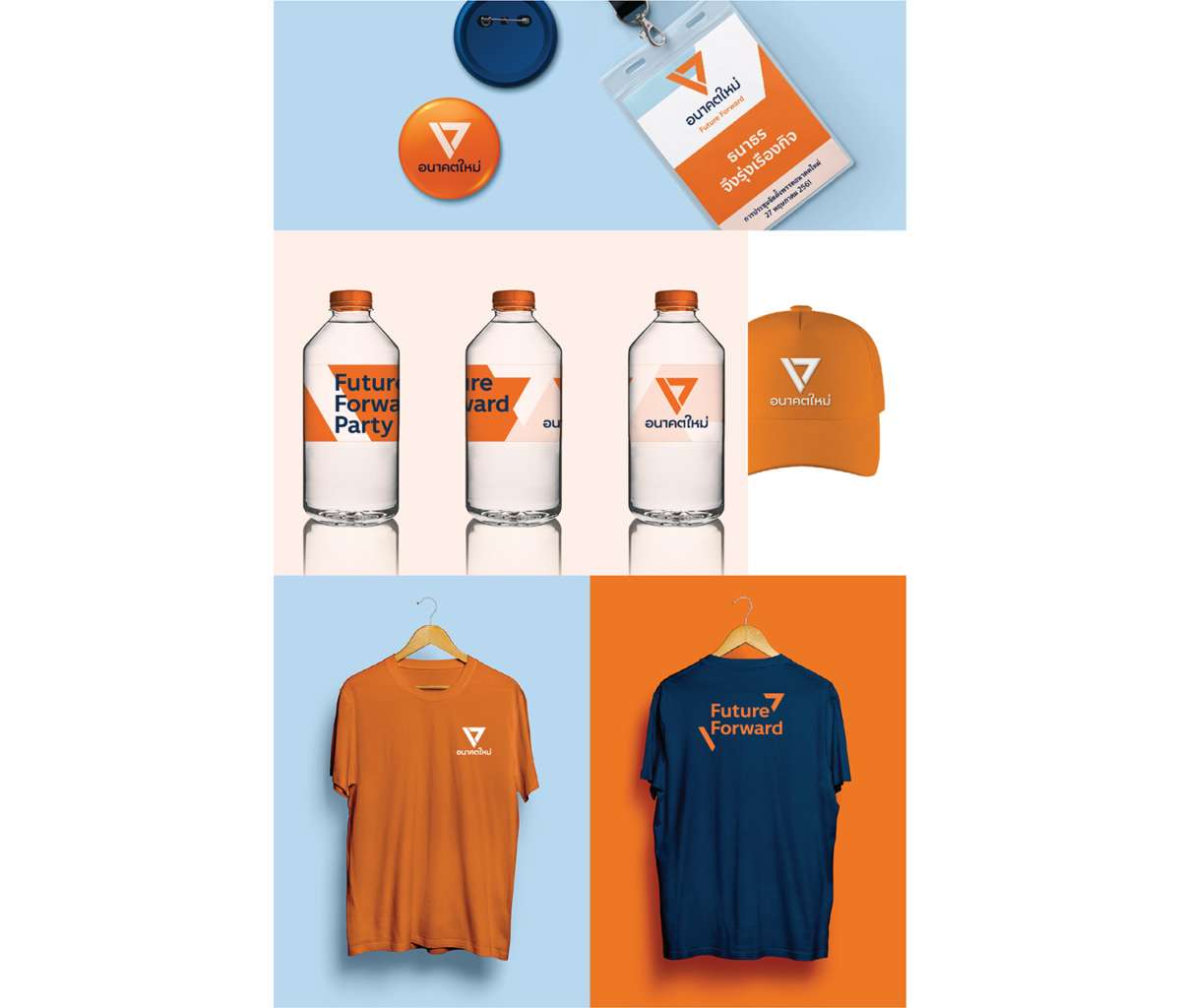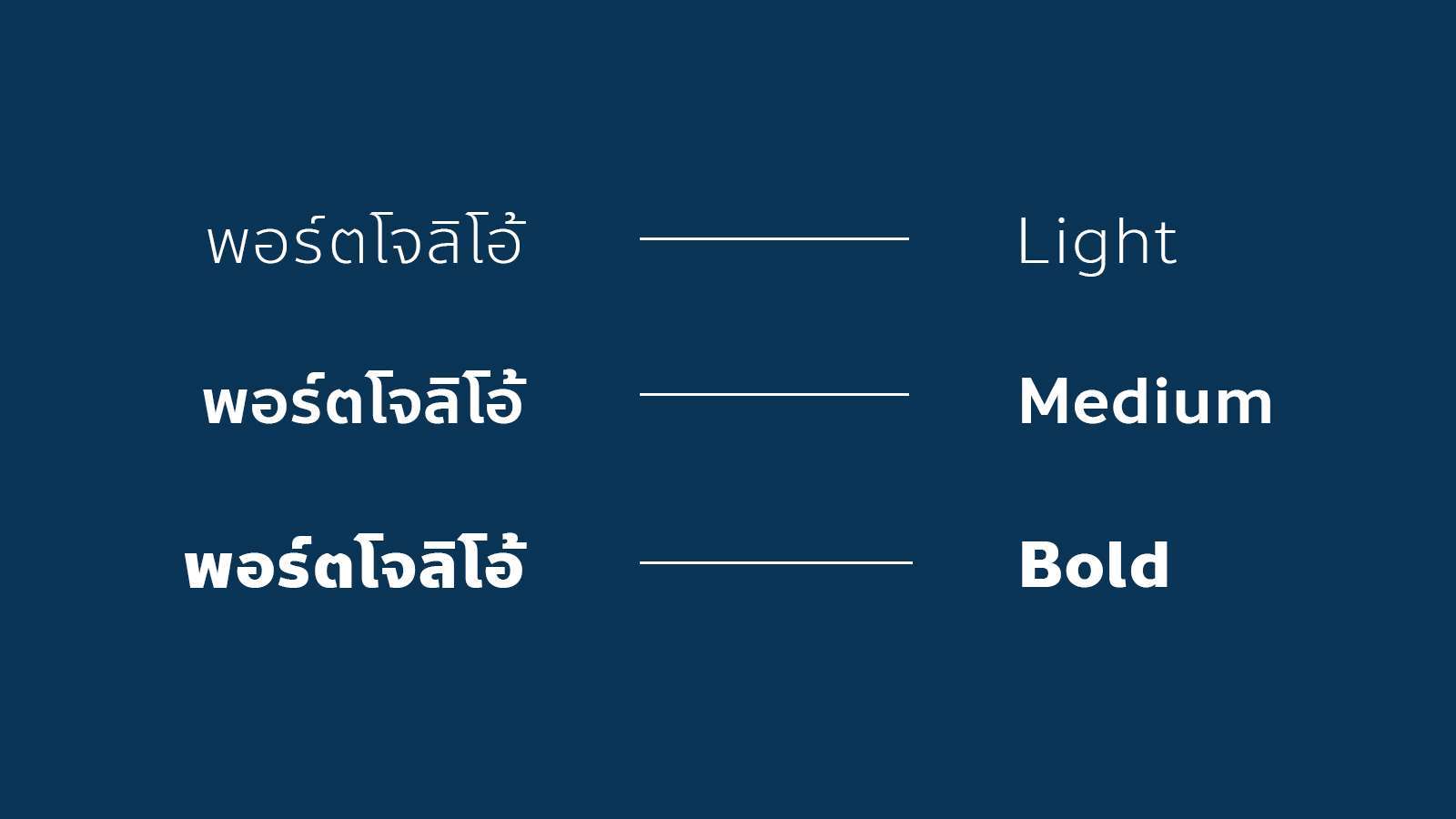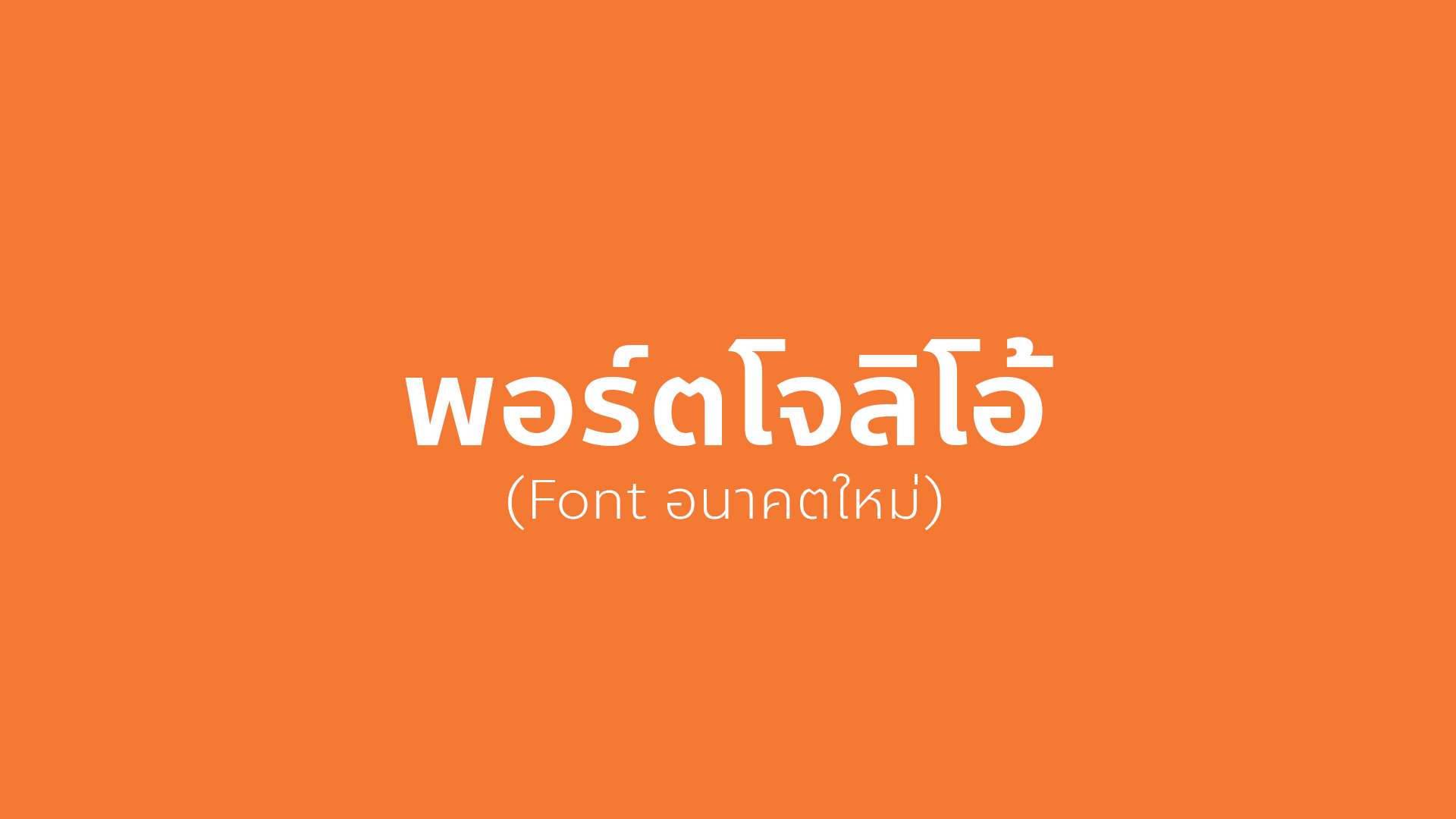
เพราะคาแรกเตอร์ที่ชัดเจน จะบ่งบอกตัวตนที่ชัดเจน หากเราเคยดูภาพยนตร์แนวเกมการเมืองมาบ้าง เราคงพอจะคุ้นเคยกับการจัดการภาพลักษณ์ของแคนดิเดต ให้เหมาะสมกับพรรคและภาพที่อยากจะสื่อออกไป ไม่ว่าจะเป็นคำทักทาย รอยยิ้ม สูท หรือแม้แต่สีเน็กไท
แต่เพราะเราเป็น Portjolio ที่ไม่ได้เชี่ยวชาญด้านแฟชั่น หรือุคลิกภาพสักเท่าไหร่ เราเลยหยิบยกอีกตัวอย่างของคาแรกเตอร์แสนจะชัดเจน ที่ถูกส่งผ่าน CI ของพรรคอนาคตใหม่ มาเป็นตัวอย่างของการฉีกกรอบแบบเดิมที่เราเคยเห็นมา
นอกจาก CI สีส้ม และโลโก้ที่ดูโมเดิร์นแล้ว อีกอย่างที่ถูกนำมาใช้อย่างชาญฉลาดคือ “ฟอนต์” ที่ดูไม่หนีจากความเป็นอนาคตใหม่เลย เพราะการออกแบบนั้นถูกคิดมาแล้วอย่างพิถีพิถัน ด้วยการเลือกใช้รูปทรงเรขาคณิตมาเป็น Based เพื่อสื่อภาพของความโมเดิร์นที่ชัดเจน
เพราะคาแรกเตอร์ที่ชัดเจน จะบ่งบอกตัวตนที่ชัดเจน แม้แต่ฟอนต์ก็สามารถบอกถึงภาพลักษณ์ขององค์กรได้ การเลือก Material แต่ละอย่างจึงเป็นสิ่งที่เราควรให้เวลาและใส่ใจกับมันด้วยเช่นกัน